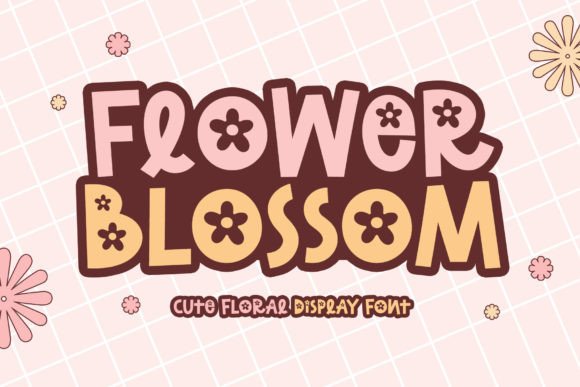
Flower Blossom
Flower Blossom – La police d’affichage qui fait éclore votre créativité
Vous cherchez une police d’affichage à la fois jolie et versatile pour vos projets design ? Flower Blossom est la réponse parfaite. Cette police décorative apporte un accent floral délicat qui se marie à merveille avec les ambiances vacances, été, automne ou même rentrée scolaire. Que vous créiez des t‑shirts, des stickers, du scrapbooking ou des supports publicitaires, Flower Blossom ajoute une touche cute et professionnelle qui capte immédiatement l’attention.
Points forts de Flower Blossom
- Design floral unique – chaque caractère intègre des motifs de fleurs qui donnent du relief à vos compositions.
- Grande lisibilité – malgré son style décoratif, la police reste claire et facile à lire, idéale pour les titres et les slogans.
- Polyvalence saisonnière – parfaite pour les thèmes summer vibes, fall vibes, les fêtes, ou les projets back‑to‑school.
- Facile à personnaliser – les lettres peuvent être combinées avec des effets de couleur, de texture ou de dégradé pour un rendu encore plus personnalisé.
Pourquoi choisir Flower Blossom pour vos créations ?
En plus d’une esthétique cute et professionnelle, Flower Blossom vous aide à :
- Renforcer l’identité visuelle de vos projets grâce à un style floral distinctif.
- Attirer l’attention sur les éléments clés comme les titres, les invitations ou les logos.
- Gagner du temps de conception grâce à une police prête à l’emploi, sans besoin de retouches complexes.
- Offrir une expérience utilisateur agréable, car les lettres restent lisibles même à petite taille.
Idées d’utilisation concrètes
- Cartes de vœux et invitations pour les fêtes d’été ou d’automne.
- Design de t‑shirts et de sweats à capuche pour les événements scolaires.
- Étiquettes, stickers et tampons pour le scrapbooking et le crafting.
- Affiches promotionnelles pour les salons, marchés artisanaux ou boutiques en ligne.
- Logos et branding de petites entreprises qui souhaitent un look doux et élégant.